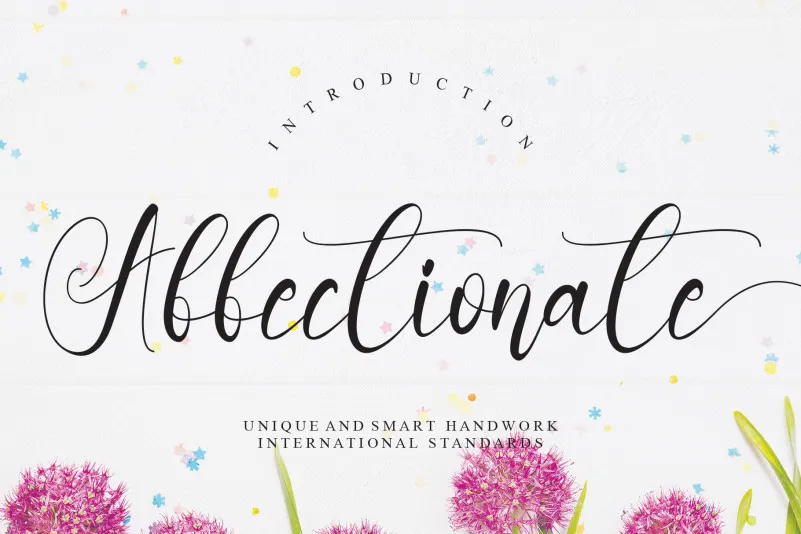
Affectionate Font – Fonte Grátis
Affectionate Font
Esta é uma fonte escrita à mão com estilo elegante e leve. Ela traz a modernidade e originalidade que sua marca precisa para se destacar, criando um design incrivelmente atraente e divertido. Ideal para aqueles projetos necessitando de personalidade extra em seu design gráfico, essa fonte ‘Affectionate Font’ criará uma sensação mágica em qualquer layout ou template. Ela é perfeita para criações como cartões de aniversário, desenhos animados, logotipos infantis e até mesmo mensagens personalizadas no Instagram. Seja qual for o seu projeto gráfico, essa fonte criará um toque único que falará diretamente ao seu público-alvo.